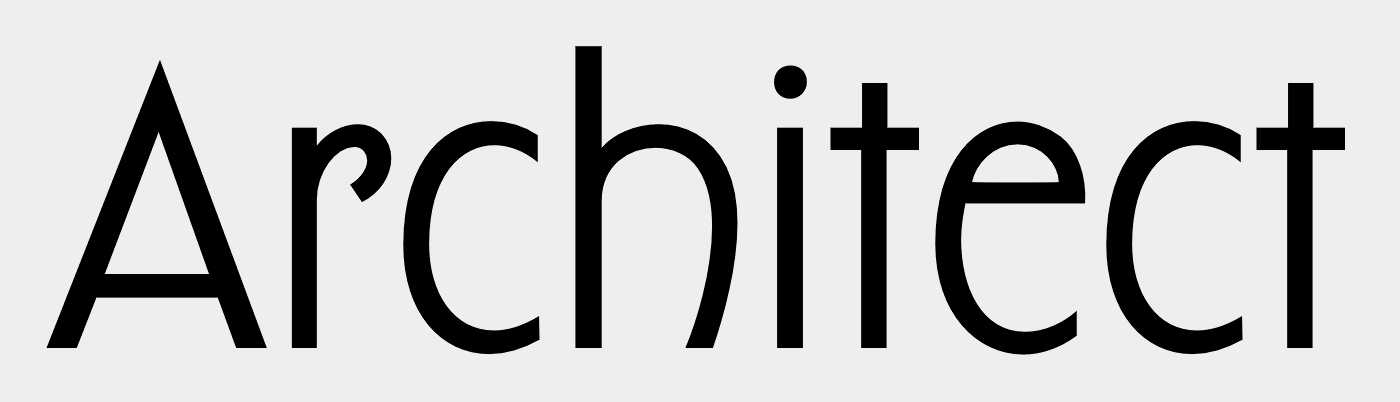
Welche Schrift? (Art déco, The Fountainhead)
kürzlich ist mir in dem Film "The Fountainhead" (Deutsch "Ein Mann wie Sprengstoff") eine Schrift aufgefallen, die ich sehr schön finde. Als interessierter Typografie- und Designlaie (und Forumsneuling) würde ich sie in die Schublade "Art déco" sortieren, obwohl das Erscheinungsjahr, 1949, vielleicht schon etwas spät für diesen Stil wäre. Sie erinnert mich auch an Schriften, die man im Zusammenhang mit dem Architekten Frank Lloyd Wright immer wieder sieht...
Handelt es sich hierbei zufällig um einen Schriftklassiker, oder kann mir jemand zumindest sagen, wie man den Stil genau nennt und welche Schriften so ähnlich aussehen?
Sicherlich sind da einige Art-Deco-Einflüsse drin und bestimmt auch gewollt. Eine besonders bekannte Interpretation solcher Schriften ist die Neutraface.
Danke für die schnelle Antwort. Die Neutraface gefällt mir auch und kommt der gesuchten Schrift für meine Begriffe schon einigermaßen nah. Aber abgesehen von dem sehr charakteristischen R in der "Fountainhead"-Schrift sehe ich noch einen deutlichen Unterschied in der Höhe der waagerechten Arme* z.B. beim H und E. Bei der Neutraface sind diese unterhalb, bei der gesuchten Schrift oberhalb der halben Versalhöhe* – das macht für das Gesamtbild viel aus, finde ich.